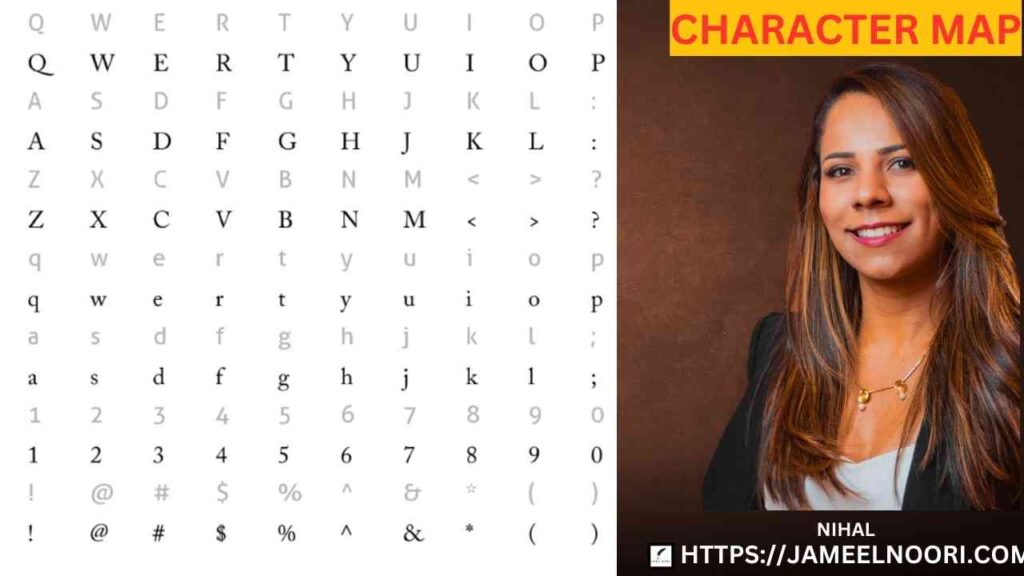
Download Urdu Font Nihal – Complete Guide
Urdu fonts aaj ke digital era me writers, students, aur designers ke liye bohot important ho gaye hain. Agar aap professional aur clear Urdu typing experience chahte hain, to Download Urdu font Nihal aap ke liye perfect choice hai.
Overview Download Urdu Font Nihal
Download Urdu font Nihal ek popular TrueType Font hai jo Pakistani users me bohot famous hai. Yeh font clean aur easy-to-read style provide karta hai, jo blogs, articles, aur graphic designs me use ho sakta hai.
Nihal font key highlights:
Features of Download Urdu Font Nihal
Download Urdu font Nihal ka sabse bada advantage uski readability aur professional design hai. Iske kuch major features ye hain:
• Clean Typography: Har character clear aur stylish hai.
• Versatile Usage: Blogs, articles, official documents aur graphic design me use ho sakta hai.
Benefits of Using Nihal Font for Urdu Writing
Download Urdu font Nihal use karne ke bohot saare faide hain:
• Professional Look: Documents aur presentations bohot professional lagte hain.
• Enhanced Readability: Readers ke liye text easy-to-read aur attractive banta hai.
In conclusion, Nihal Urdu Font is a stylish and user-friendly typeface that enhances Urdu writing with clarity and beauty. It is fully compatible with Windows, Mac, and mobile devices, making it an excellent choice for personal, educational, and professional projects. Whether you are designing, publishing, or simply typing in Urdu, Nihal Font ensures a smooth and elegant experience for all users in Pakistan.
Is Nihal font suitable for graphic design?
Absolutely, Nihal font ki clean typography graphic design projects ke liye perfect hai.